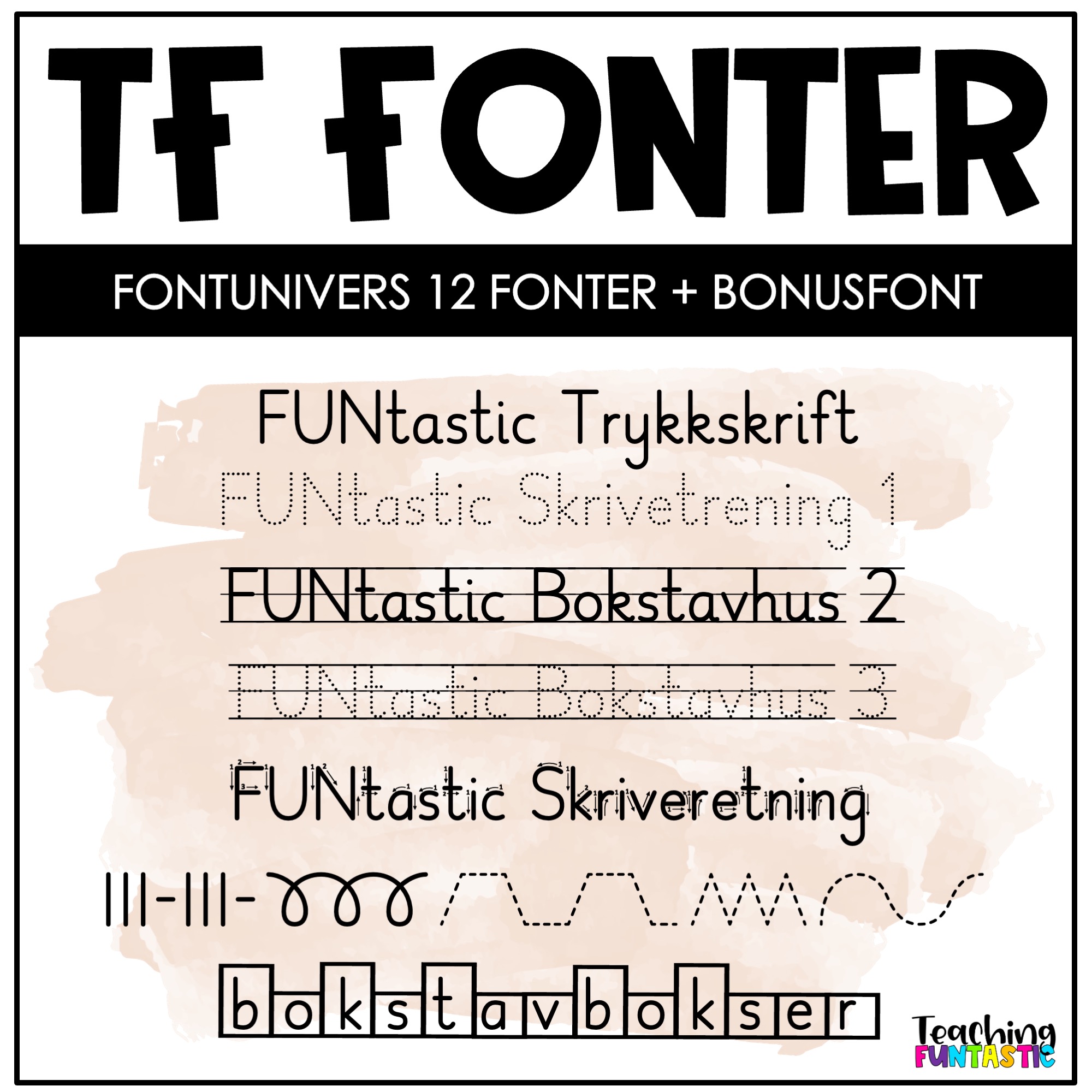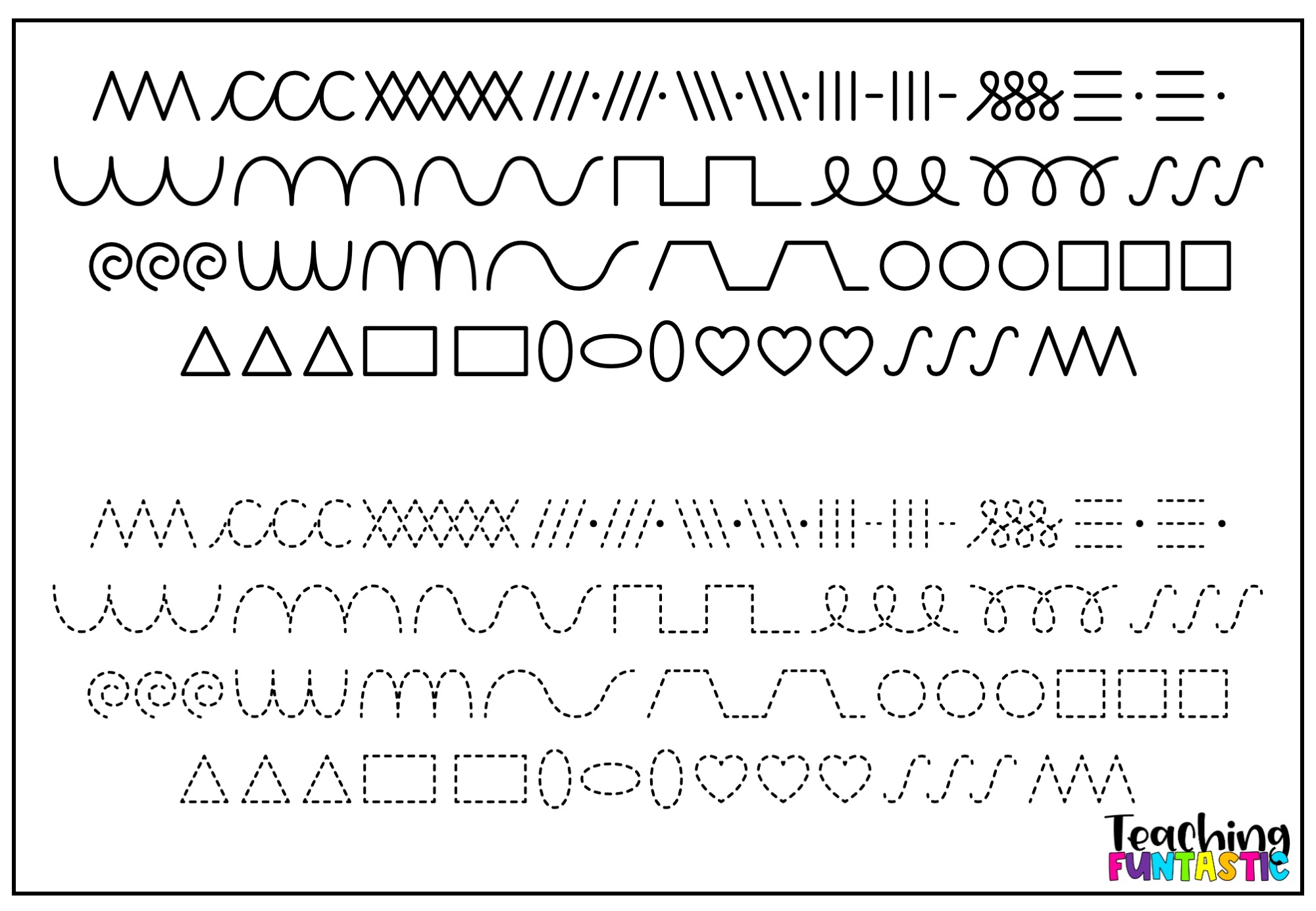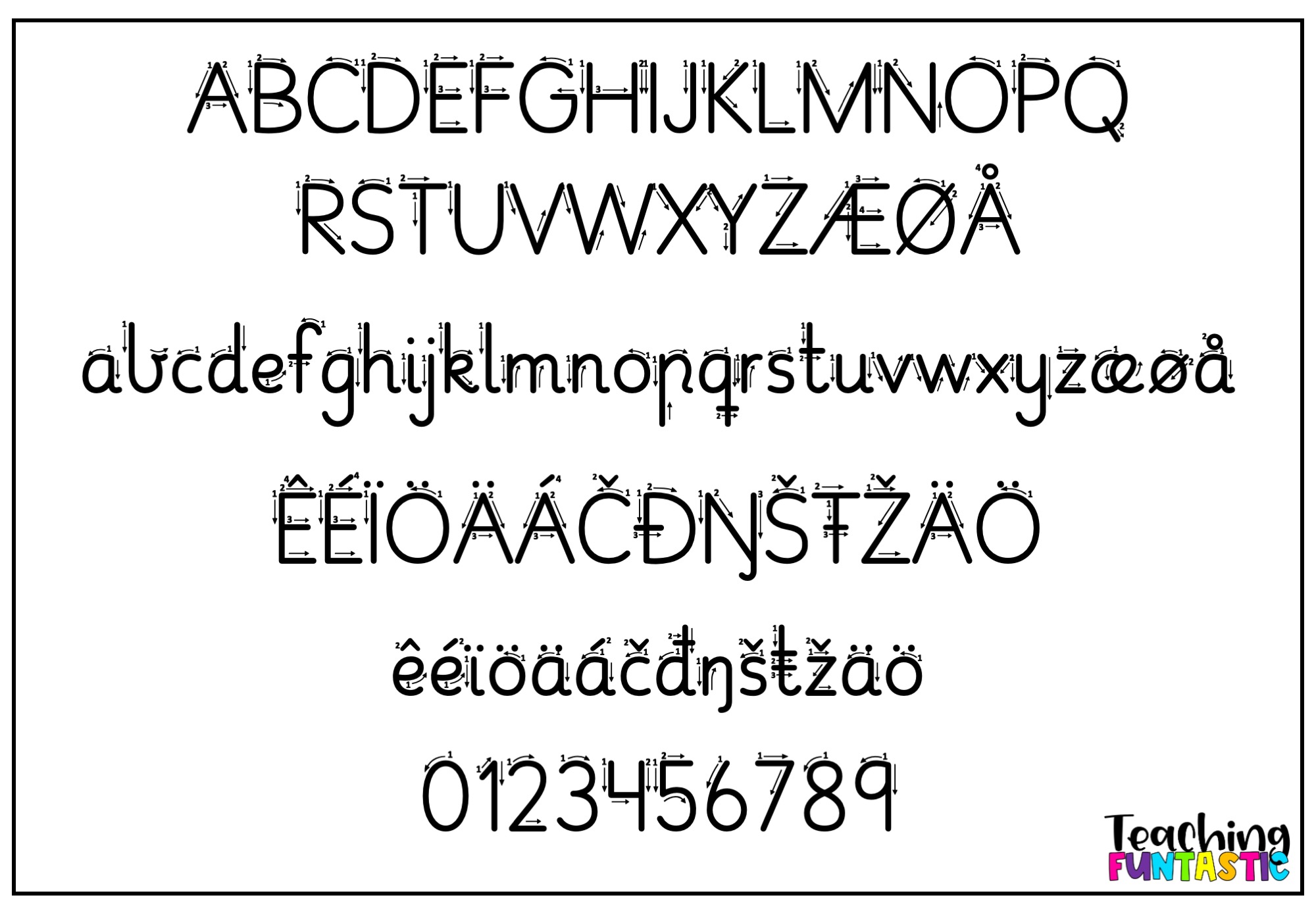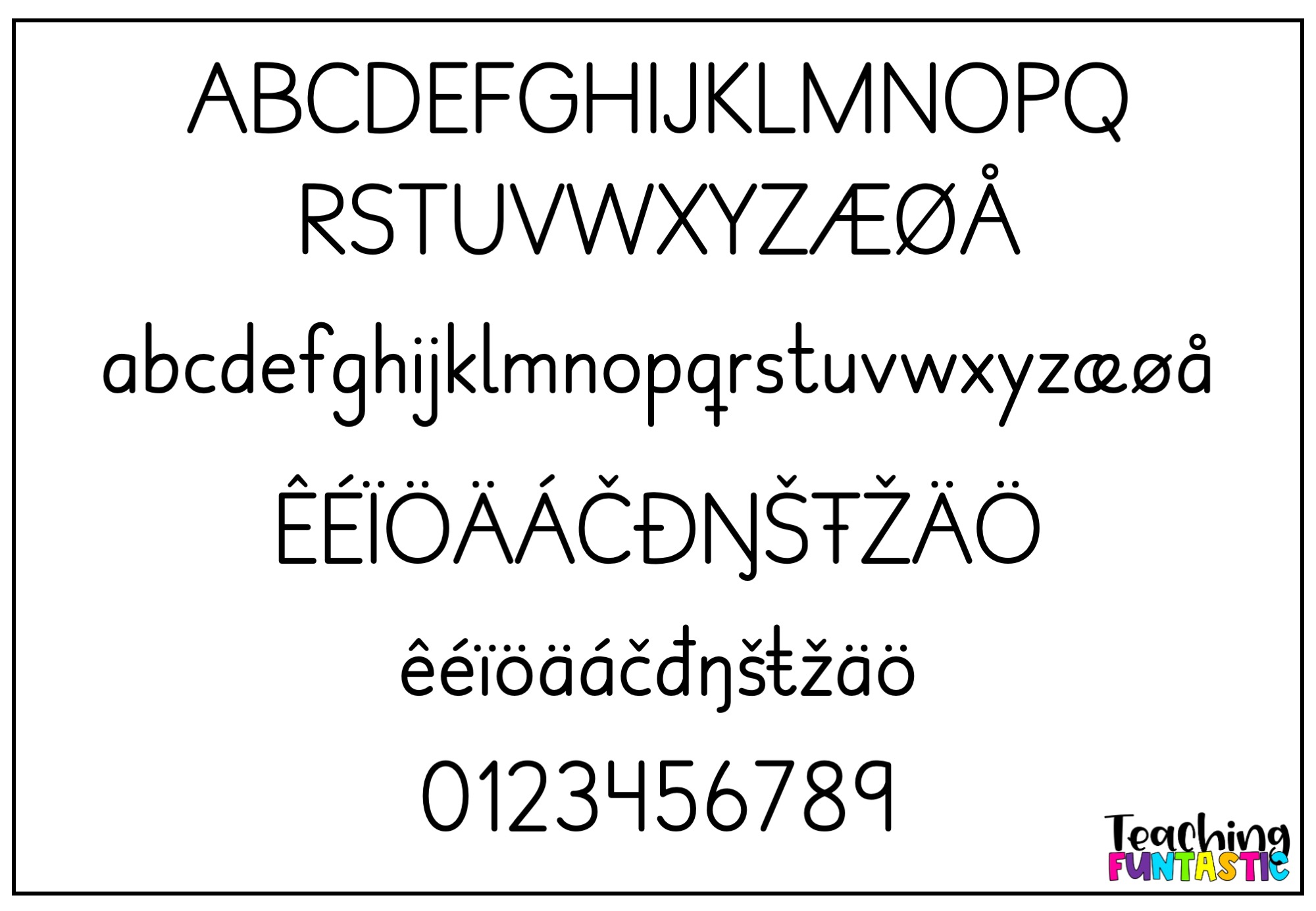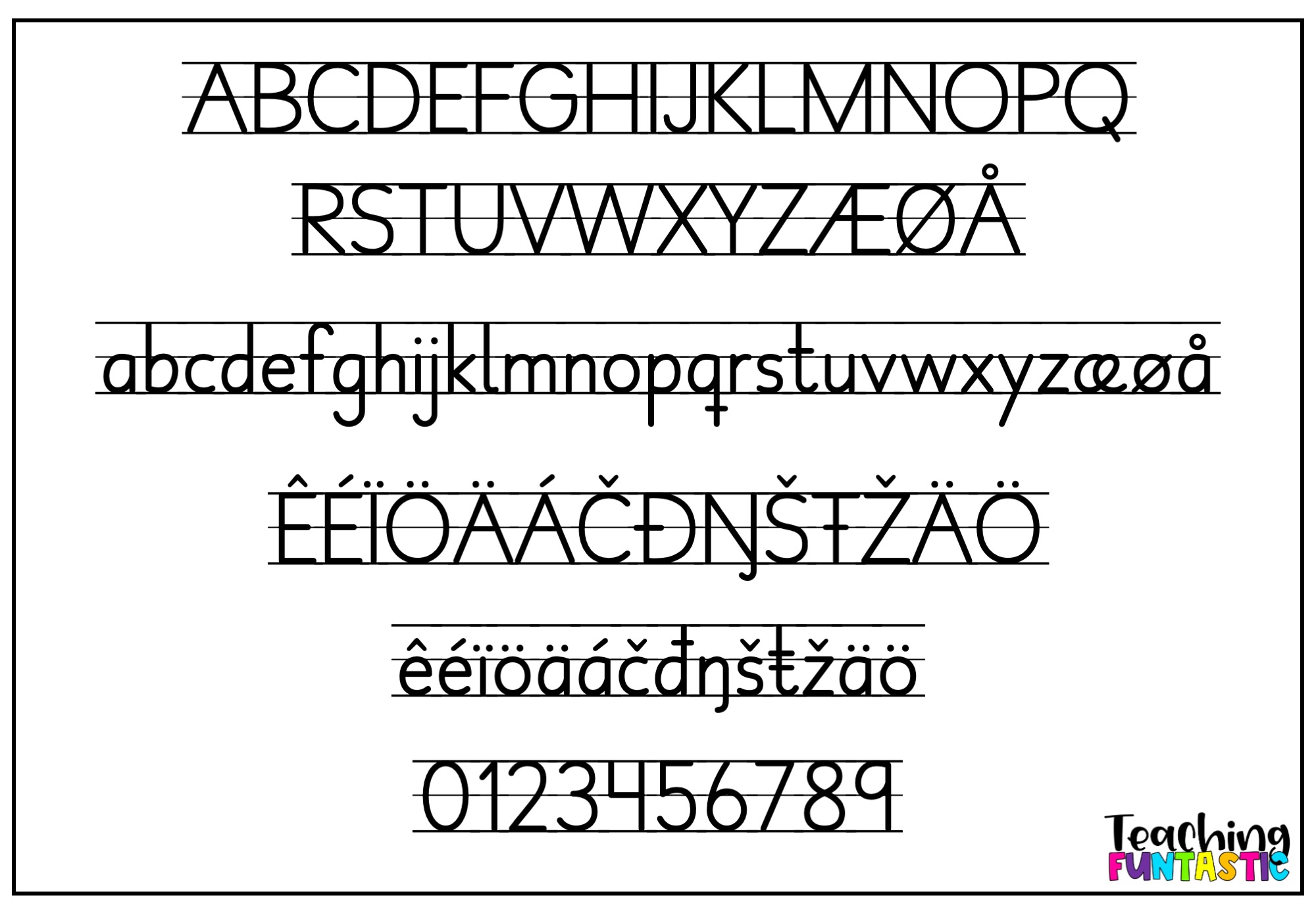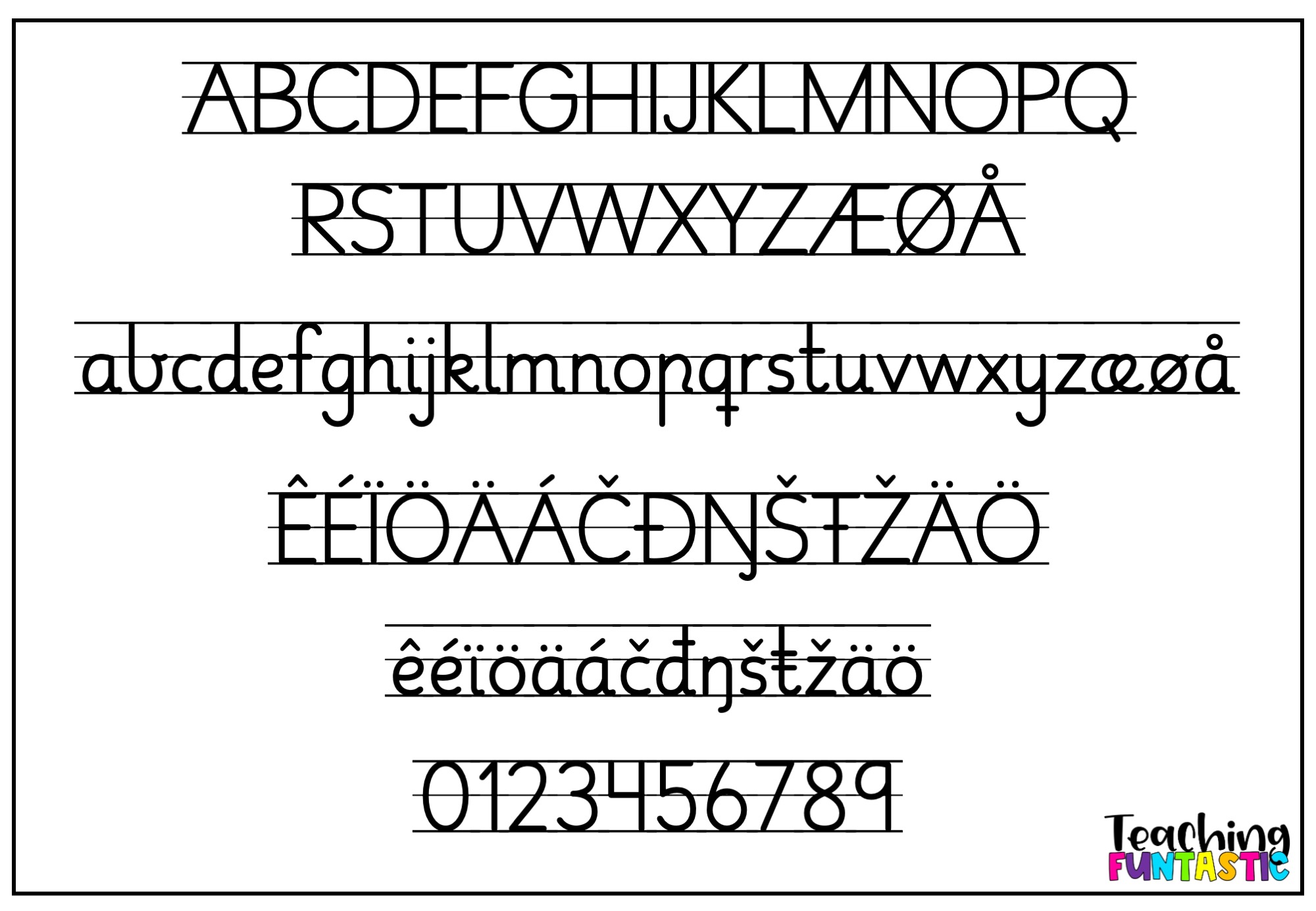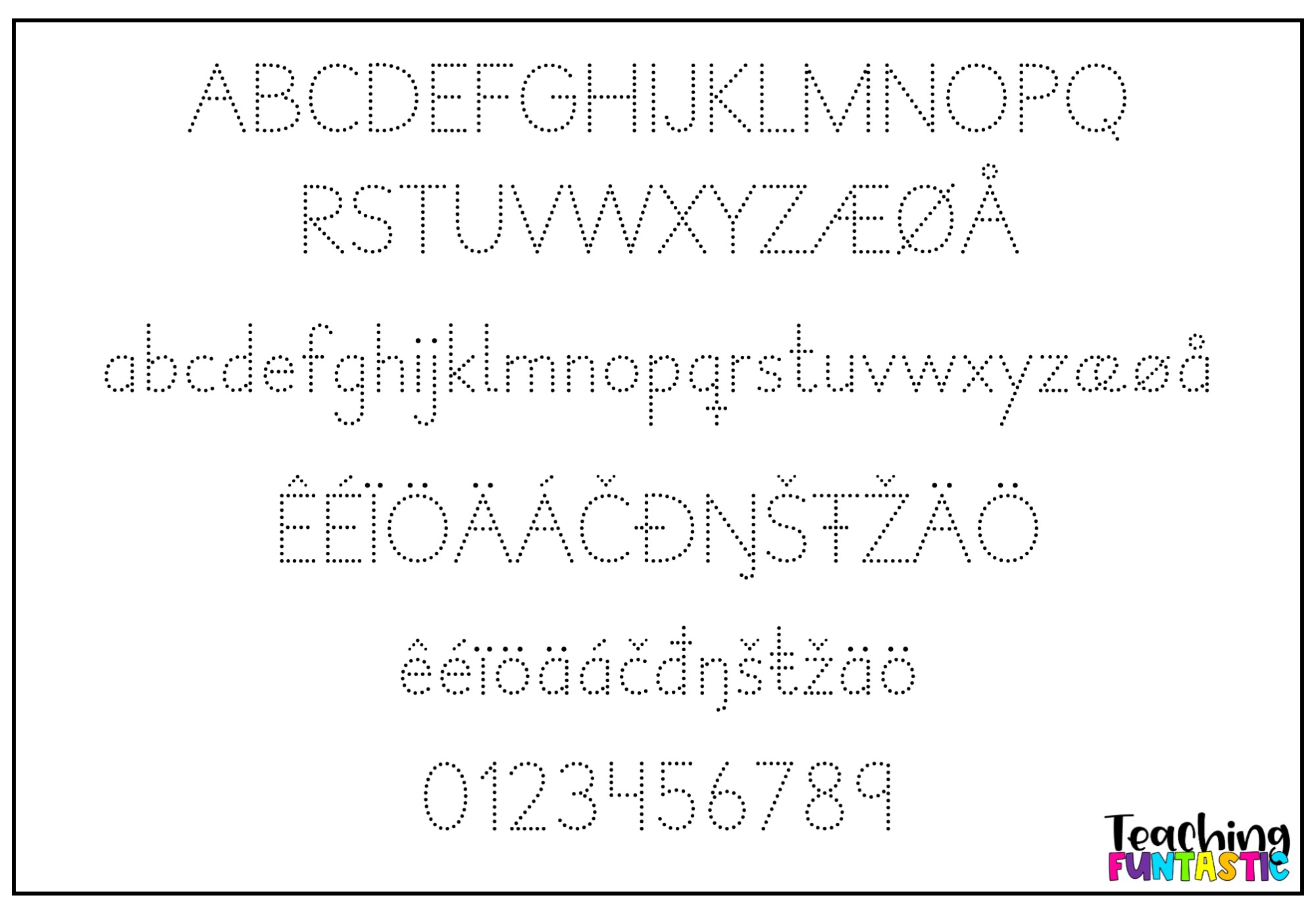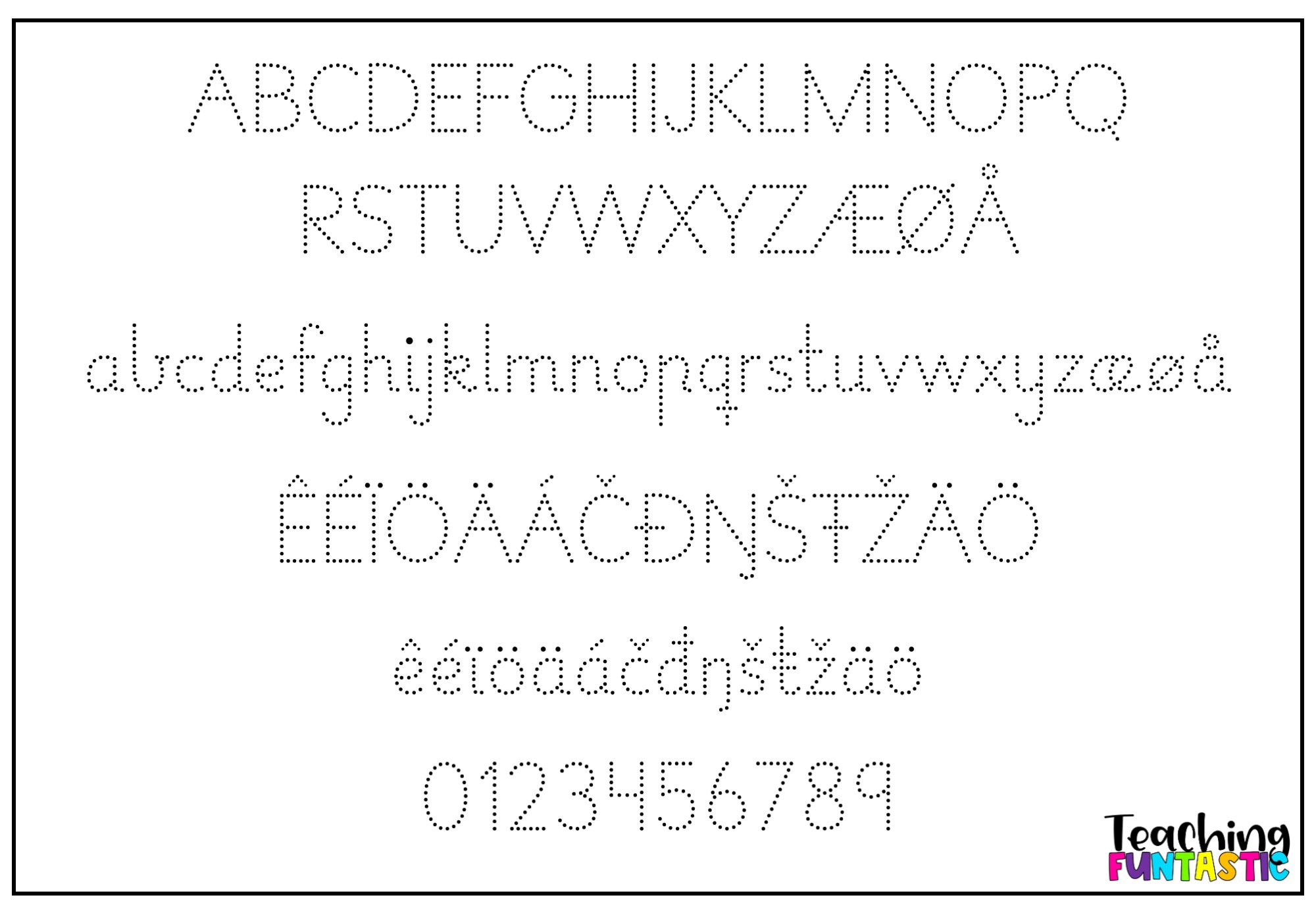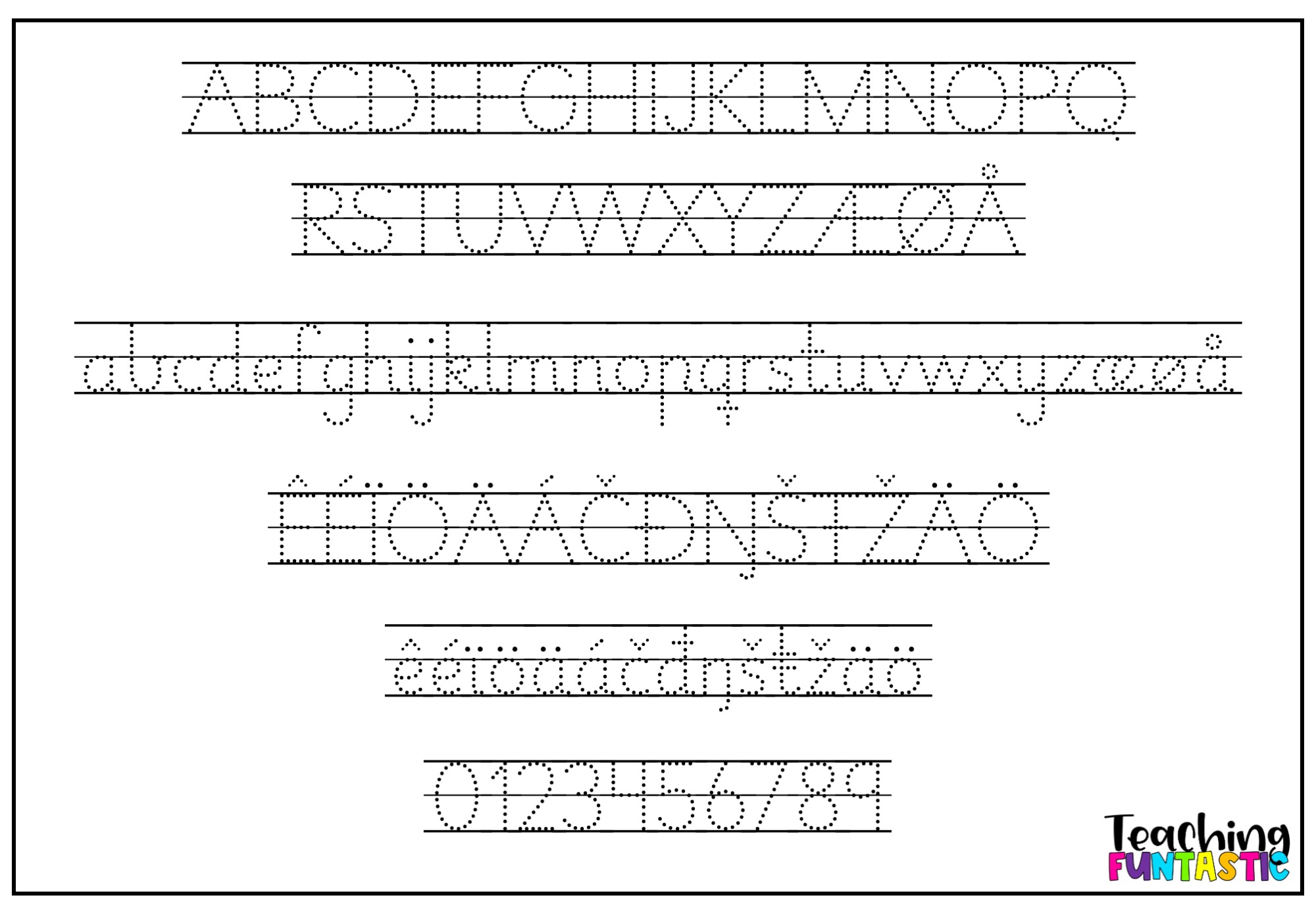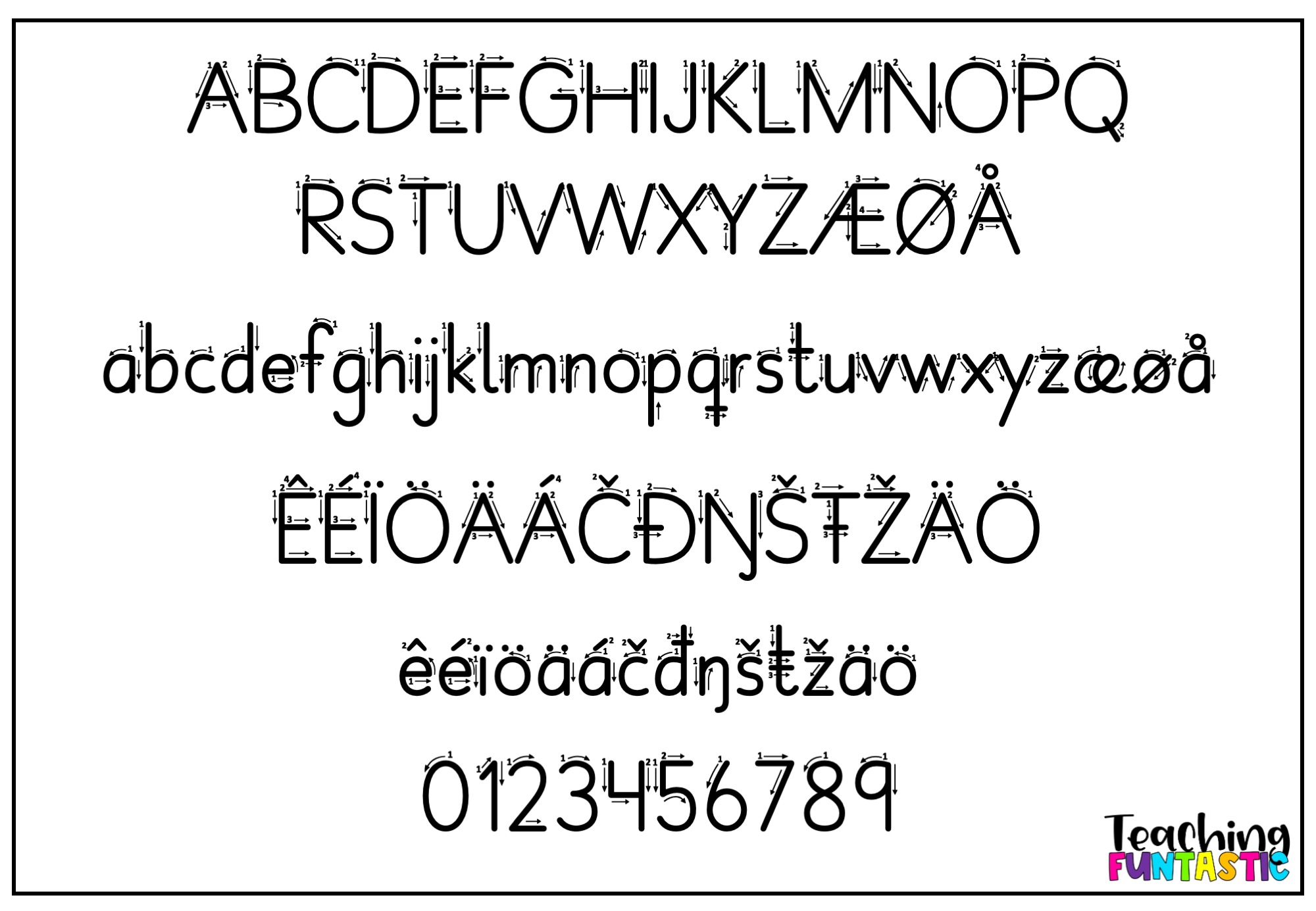
FUNtastic Font-universet – komplett font håndskrift-pakke for lærere og skoler
FUNtastic Font-universet er den ultimate samlingen av undervisningsvennlige fonter – laget spesielt for lærere i grunnskolen. Pakken består av 12 fonter + en bonusfont, og gir deg alt du trenger for å lage profesjonelt, helhetlig og visuelt tiltalende undervisningsmateriell.
Her finner du alt fra trykkskrift, stiplet håndskrift, skriveretningsfont, bokstavbokser og finmotorikk-border – til en eksklusiv matematikkfont som gjør oppgavelaging superenkel.
Hele fontfamilien – laget for norske og samiske elever
Fontene inneholder alle norske og samiske bokstaver (æ, ø, å, á, č, đ, ï, ŋ, š, ŧ, ž) – noe som er sjelden å finne i kommersielle fonter.
Hver font følger de bokstavformene elevene lærer å skrive i norsk skole, ikke amerikansk eller britisk skrivestil. Du velger selv den varianten som passer best for din klasse – enten bokstaver med rette linjer eller med små “haler” som gjør det lettere å koble sammen bokstavene senere dersom elevene skal lære sammenhengende skrift.
Fontene er dessuten rene, enkle og lettleste, noe som gjør dem svært godt egnet for lesesvake elever og elever med lesevansker. Den tydelige og konsekvente bokstavformen gir trygghet og gjenkjenning i både lesing og skriving.
Bonus: Matematikkfont
Som eksklusiv bonus får du FUNtastic Matematikkfonten, laget for deg som lager regneoppgaver i Word. Her kan du for eksempel skrive x for å automatisk få det norske multiplikasjonstegnet ∙. Det gjør det lekende lett å lage pene og korrekte matematikkoppgaver uten spesialsymboler. Brøkoppgaver skrives også enkelt ved å taste inn feks. 2/3, og det vil automatisk endres til en brøk slik vi lære elevene å skrive dem.